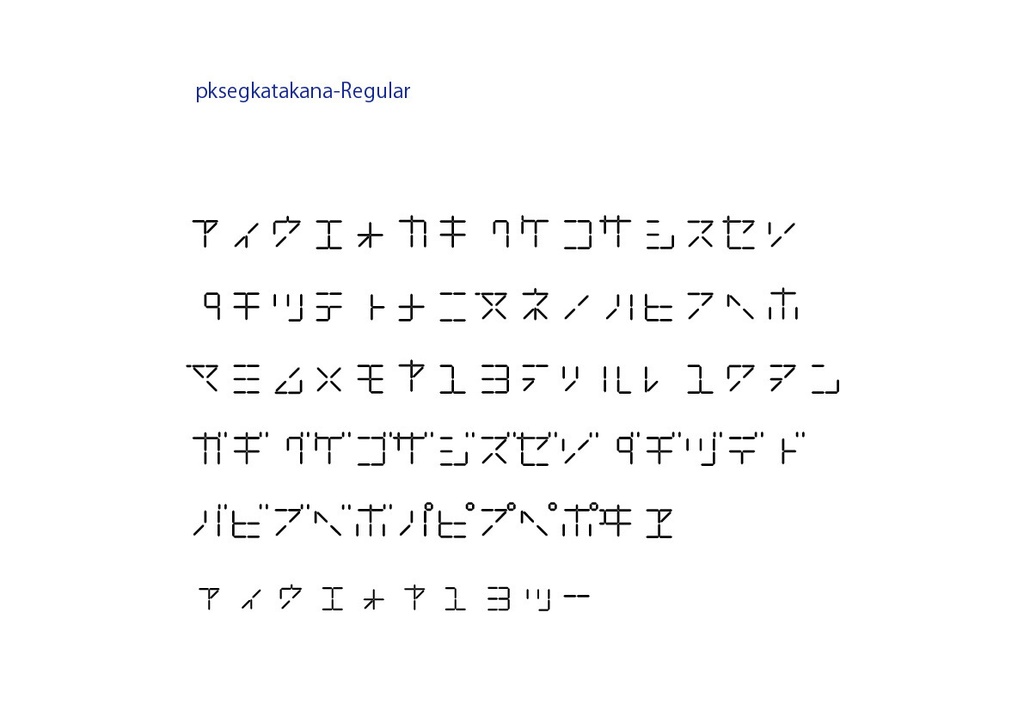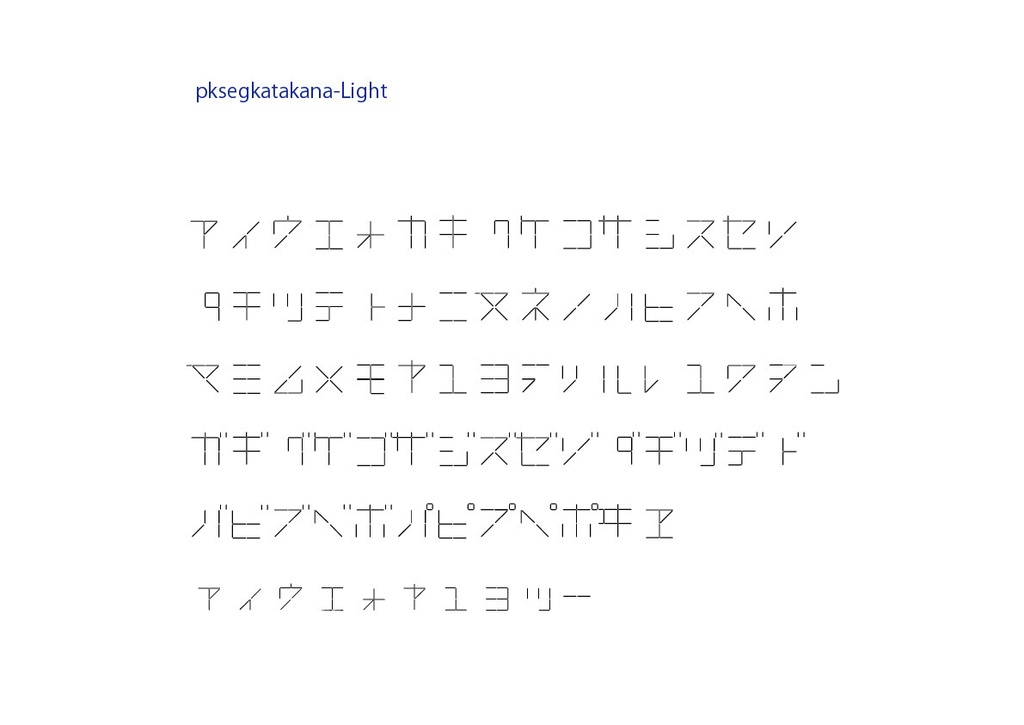
デジダルコンテンツ 20seg.カタカナフォント
20セグメントのLED表示風のカタカナフォントです。 RegularとLightの2種類を同梱しました。 架空の20(+濁音半濁音用の4)セグメントLEDを想定し、これによって表示されるカタカナのフォントを作成しました。 【収録文字】 アイウエオカキクケコサシスセソタチツテトナニヌネノハヒフヘホマミムメモヤユヨラリルレロワヰヱヲン ガギグゲゴザジズゼゾダヂヅデドバビブベボパピプペポ ヴ ァィゥェォャュョッ 長音(ー) 【データ内容・使用方法】 zipファイルを解凍してください。 OTFファイル pksegkatakana-Regular.otf(標準) pksegkatakana-Light.otf(細字) JPGファイル(カタカナ表示の見本) pksegkatakana-Regular.jpg(標準) pksegkatakana-Light.jpg(細字) テキストファイル readme.txt が収録されています。 pksegkatakana-Regular.otf と pksegkatakana-Light.otf のどちらか、または両方をインストールしてください。 【購入の際の注意点】 商用利用OKです。 使用した場合、ご一報いただけるとうれしいです。Twitterなどで紹介します。 フォントファイルの改変・再配布は禁止です。 ※追記 2021.9.20 ファイル名を pk20segkatakana から pksegkatakana に変更しました。 Word、Excelでもフォントを選ぶ際にフォント名が表示されるようにしました。